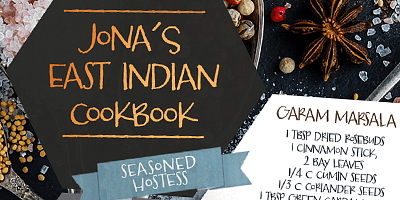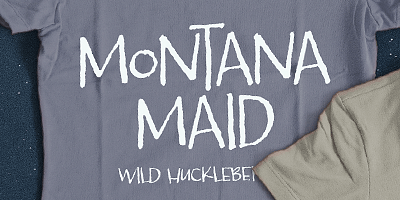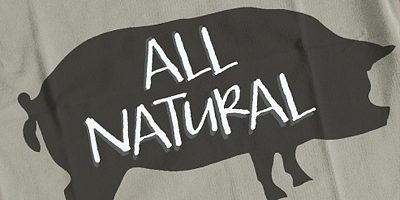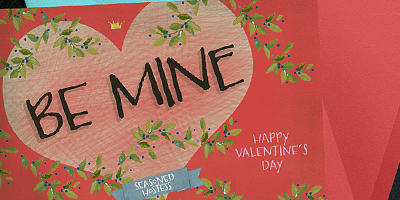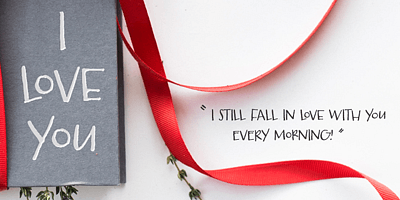
Seasoned Hostess si basa su lettere personalizzate progettate per un sistema di segnaletica per ristoranti. Un font monocase semplice e di facile lettura con glifi alternativi che replicano lettere casual scritte a mano. È un piacere da usare nella stampa e nelle app online.